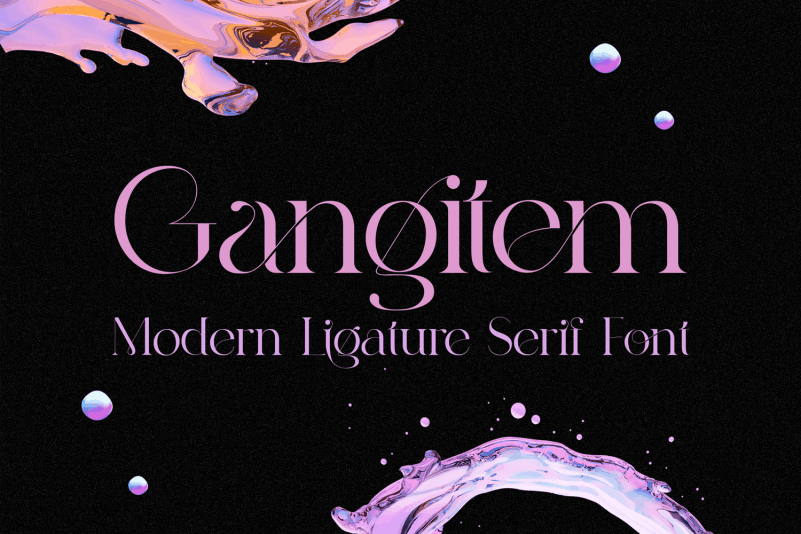
Introduzimos a Gangitem Serif Font, uma fonte serif moderna e elegante equipada com várias ligaturas discentes para oferecer tudo que você precisa para um excelente tipografia. Ela é tanto moderna quanto nostálgica e funciona muito bem para logomarcas, mastheads e pull quotes. A Gangitem Serif é perfeitamente complementada por uma fonte sans-serif ou script leve. Esta fonte 177Studio se destaca como uma opção de qualidade para qualquer projeto gráfico que exija um toque de elegância clássica ao mesmo tempo em que permanece atual e moderna. Não hesite em experimentar a Gangitem Serif para adicionar aquela pitada de sofisticação aos seus projetos.